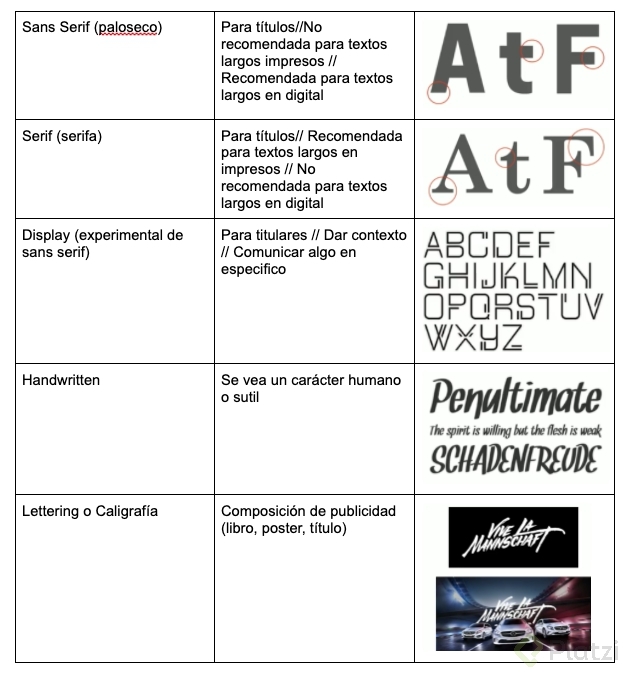
Selección de Tipografía en Proyectos Editoriales
La tipografía es la representación gráfica del lenguaje conformada por caracteres intercambiables que funcionan como un sistema, ya sea físico o digital.
Recomendaciones para elegir la tipografía adecuada
- Debe tener las variables que necesitas (pesos visuales como Black, light, etc)
- Debe tener el repertorio suficiente para el idioma o uso que necesitas. Para el español es indispensable contar con tildes o la ñ.
- Se debe ver muy bien en un contexto real.
- Debes asegurarte que la tipografía tenga el estilo particular que buscas.